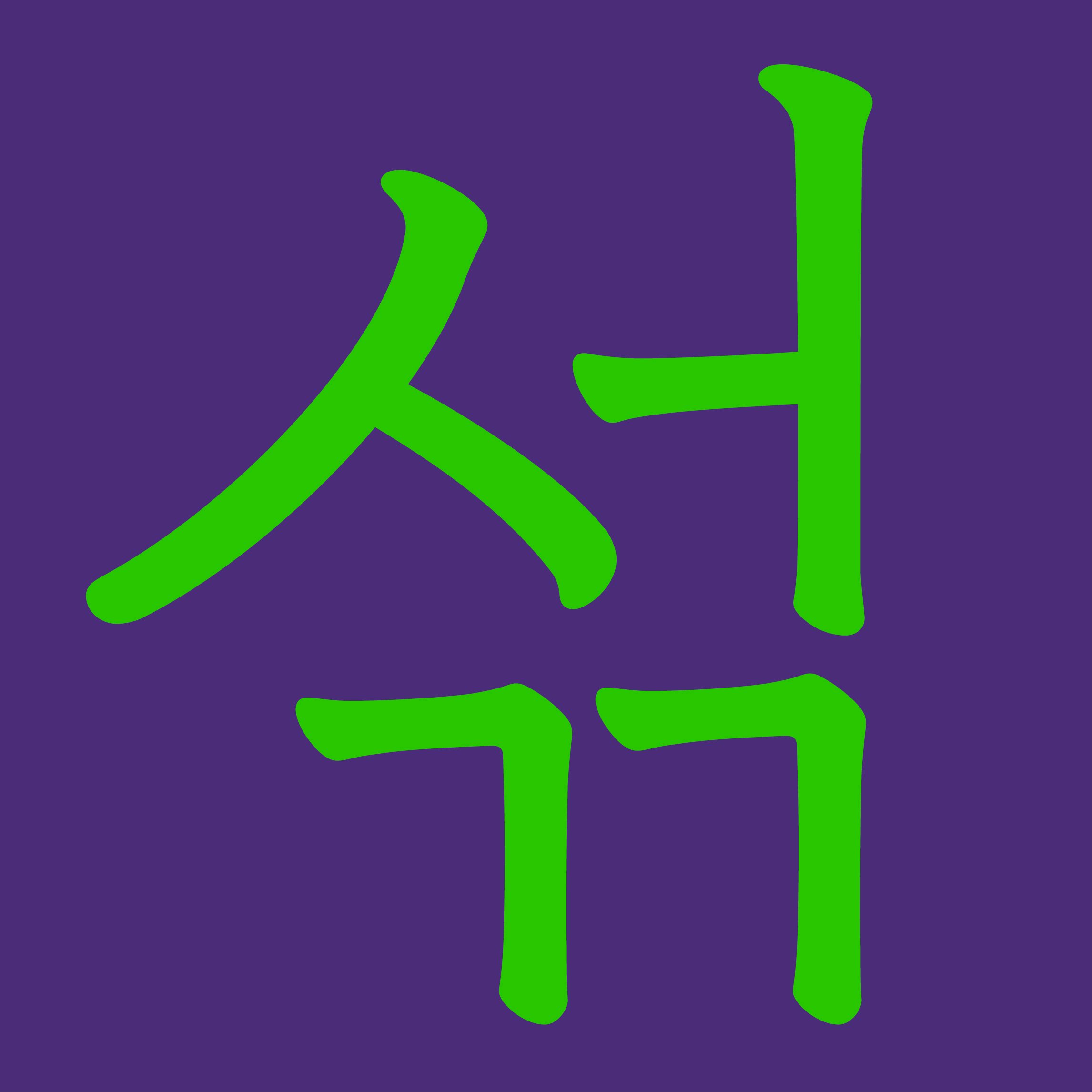
Sandoll 정체
산돌 정체는 기존 본문 서체의 아쉬운 점을 찾고 분명한 설계 목적과 명확한 조판 방법을 제시하여 쓰기 좋은 본문 서체를 개발하는 것에서부터 출발했다.
글자끼리 변별력을 높이는 뼈대 설계와 뚜렷한 점, 획의 윤곽을 추구했으며, 하나의 정체성을 유지하며 다양한 분위기를 내도록 뼈대, 무게, 너비를 축으로 글자가족이 확장된다. 이름 뒤에 붙은 세자리 숫자의 첫 번째 자리인 뼈대는 시대성을 나타내며 숫자가 높을수록 현대적인 분위기를 띠며, 두 번째 자리인 무게는 숫자가 높을수록 굵어진다. 세 번째 자리인 너비는 숫자가 낮을수록 좁아진다.
한글뿐만 아니라 라틴 확장 영역까지 제작해 라틴 문화권 35개 국어를 표현할 수 있다. 자족 뒤에 붙은 i는 이탤릭을 뜻하는 것으로 이탤릭체는 라틴만 표현 가능하다.
- Sandoll 정체 / Sandoll Jeongche